2023 年 15 种最佳明星字体(免费和高级)
已发表: 2023-09-21您是一名平面设计师,正在寻找完美的字体来提升您的项目设计吗? 别再犹豫了!
在这篇博文中,我们将推出 2023 年 15 款最佳明星字体,包括免费和付费字体,它们一定能为您的设计增添一抹魔力。
您可能想知道,为什么要使用星号字体? 嗯,星星长期以来一直是灵感、辉煌和奇迹的象征。 通过将这些星星字体融入您的设计中,您可以创造出真正脱颖而出的迷人而神圣的美感。
现在,让我们深入探索星形字体的精彩世界! 在本文中,我们不仅将探讨前 15 名明星字体,还将为您提供一些有趣的统计数据和事实,以帮助您更好地了解它们的影响。
您是否知道将明星元素融入您的设计中可以将用户参与度提高高达 40%? 这是一个引人注目的统计数据,展示了星形字体的力量及其吸引观众的能力。
无论您正在制作徽标、网站还是任何其他设计项目,星号字体都可能是让您的工作更上一层楼的缺失要素。
那么,您对本文有何期待? 我们将展示一系列免费和付费的明星字体,以满足每个设计师的需求和预算。
从优雅简约的选择到大胆引人注目的设计,每种风格和偏好都有适合的明星字体。 准备好获得灵感吧,我们将带您踏上 2023 年最出色字体的旅程。
因此,事不宜迟,让我们深入研究星形字体的世界,并发现它们为您的设计项目带来的可能性。
最佳优质星星字体
希望将您的平面设计项目提升到一个新的水平? 我们精心挑选的最佳优质明星字体就是您的最佳选择。
这些字体一定会为您的设计增添额外的魔力和精致感。 不要错过,请查看下面我们为您准备的令人难以置信的选项!
新星
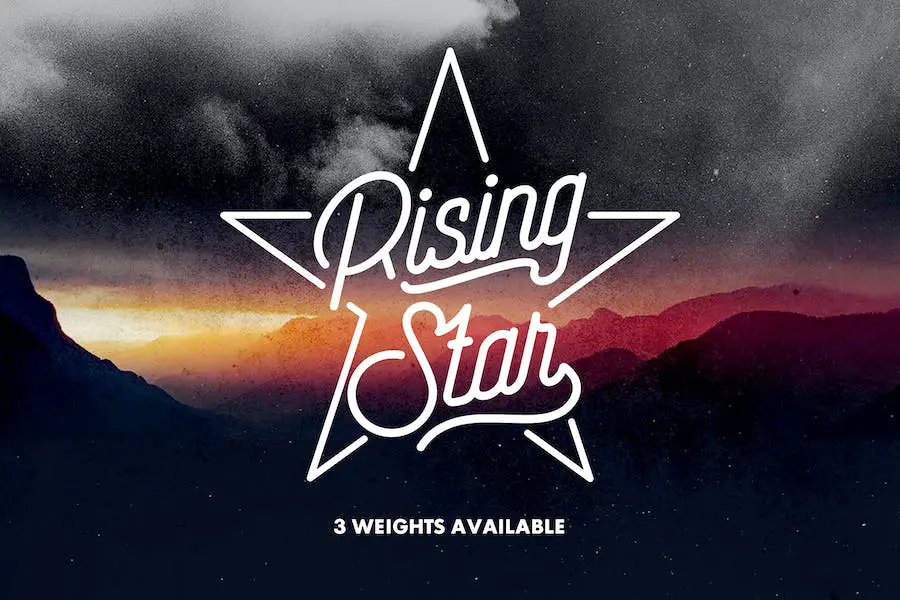
Rising Star 是一种现代单行脚本字体,捕捉了怀旧夏令营的冒险精神。 它具有常规、浅色和印花三种风格,为各种设计项目提供了多功能性。
无论您是设计网站、海报、菜单还是包装,这种字体都是完美的选择。 它结合了友好和坚固的设计以及发表声明的能力。 但它的与众不同之处在于它给任何项目带来的乐趣和兴奋。
准备好点燃您的创造力,并通过 Rising Star 为您的设计带来一丝夏日怀旧气息。
死星
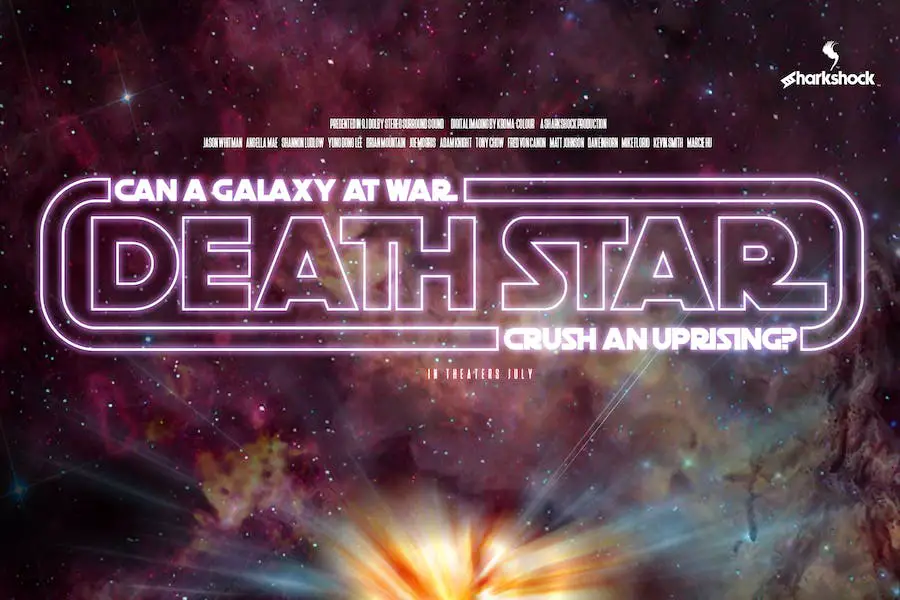
死星字体可以将您带到遥远的星系,并为您的项目提供超凡脱俗的设计。
这种全大写显示字体的灵感来自 80 年代的经典风格,具有几何圆形曲线和有限的笔画宽度变化。 它是为您的博客、徽标或 T 恤增添复古气息的完美选择。
凭借其有限的基本拉丁字符和标点符号,死星字体使事情变得简单和时尚。
星星
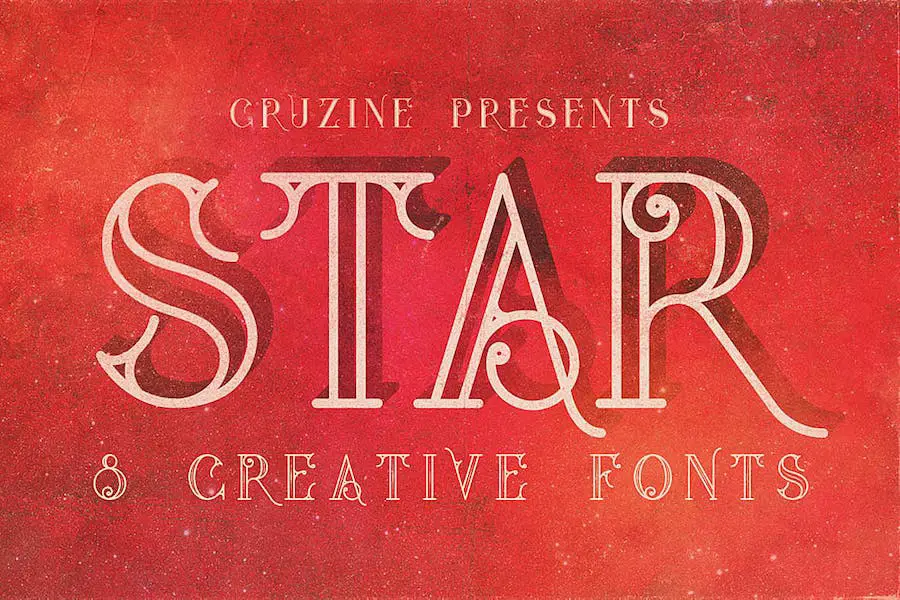
Star 是一种装饰艺术复古风格的显示或衬线字体,将为您的新项目增添一丝优雅。 无论您是从事现代设计还是创造具有复古/复古氛围的东西,Star 都能满足您的需求。
有 8 种字体文件可供选择,包括常规、grunge、内联、内联垃圾、粗体、粗体垃圾、粗体内联和粗体内联垃圾,您将有大量选项可供使用并找到最适合您的项目的字体文件。
星光
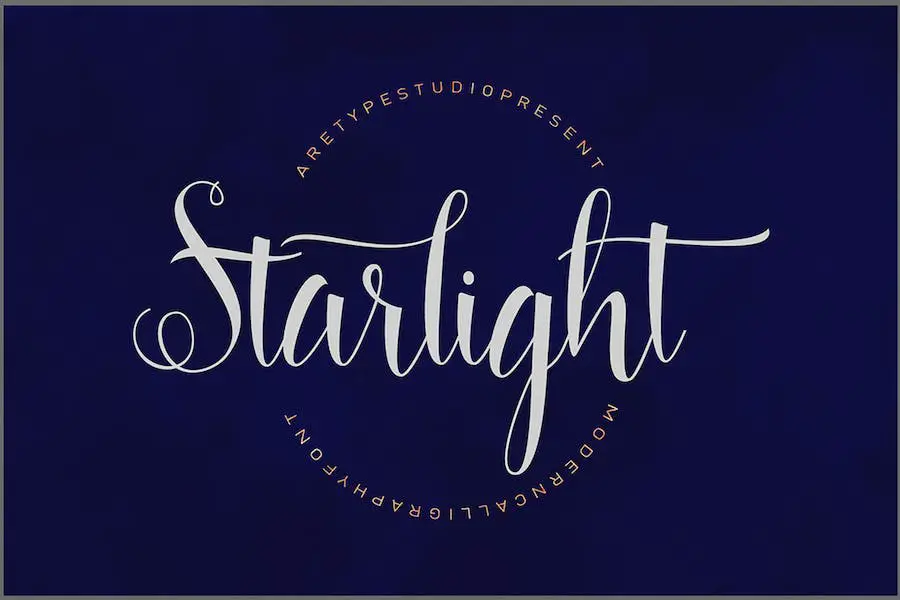
Starlight 是一种华丽的书法手稿字体,可为任何项目增添现代感。 这种字体充满活力且令人惊叹,优雅的花饰增添了一丝精致。
无论您需要签名、标题、徽标、婚礼请柬还是任何其他设计元素,星光都是完美的选择。 它还可用于时事通讯、信笺、标牌、标签、海报和徽章。
追星
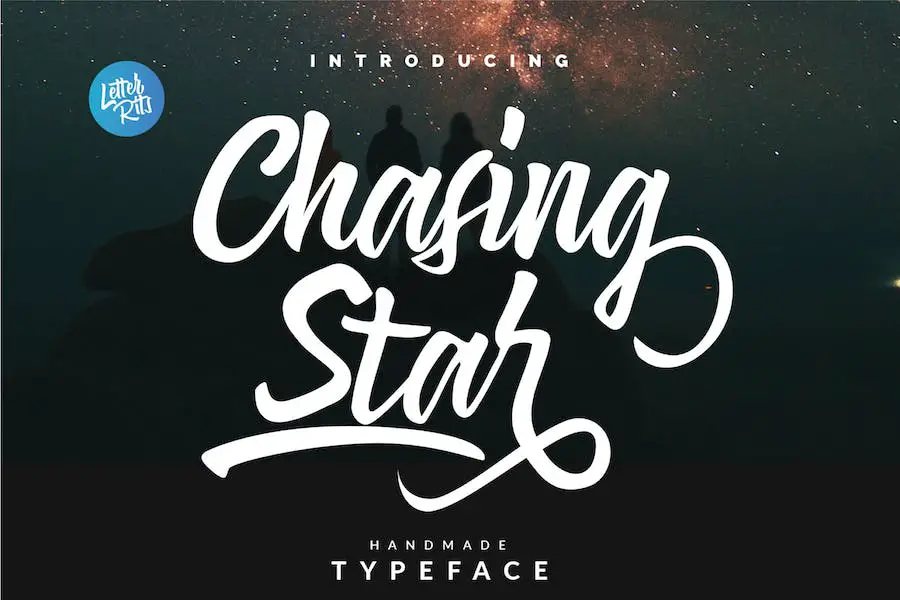
追星字体是一种多功能字体,为图形设计师提供了多种选择。 它包括大小写字母、数字、标点符号、符号和多语言字符,使其适用于广泛的项目。
无论您从事现代还是复古风格的设计,Chasing Star Font 都能为您的项目带来清新时尚的字体风格。
追星字体的关键属性之一是它适合品牌项目。 如果您想创建一个独特且令人难忘的品牌标识,这种字体可以帮助您实现这一目标。
洛维利亚星
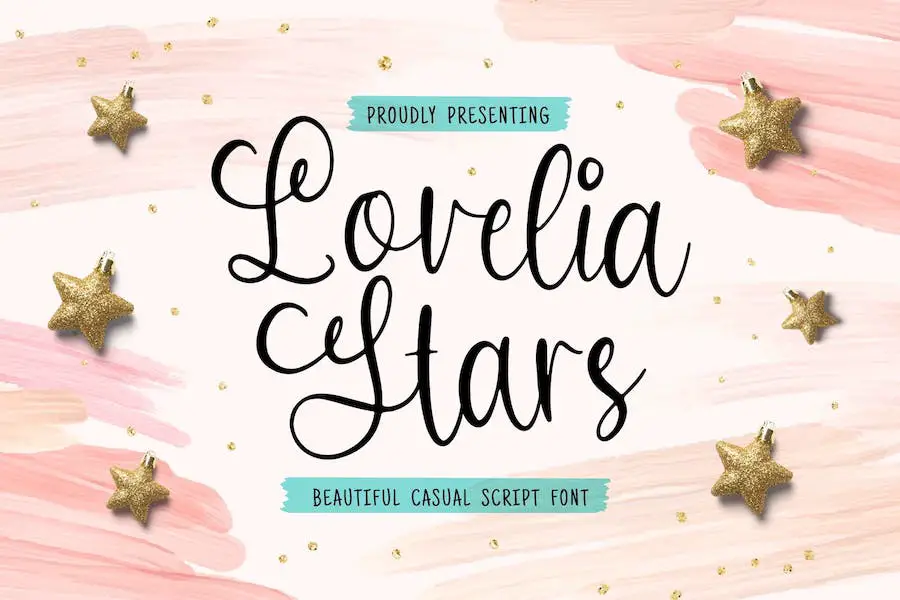
Lovelia Stars 是一种多功能字体,可以通过多种方式增强您的设计项目。
它非常适合创建醒目的徽标和品牌材料、为您的摄影添加独特的触感、制作令人惊叹的邀请函、为您的创作添加水印、制作引人注目的广告、增强产品包装以及为特殊活动增添一丝魔力。
这种字体可以满足您的所有创意需求及其他需求。
奇迹之星
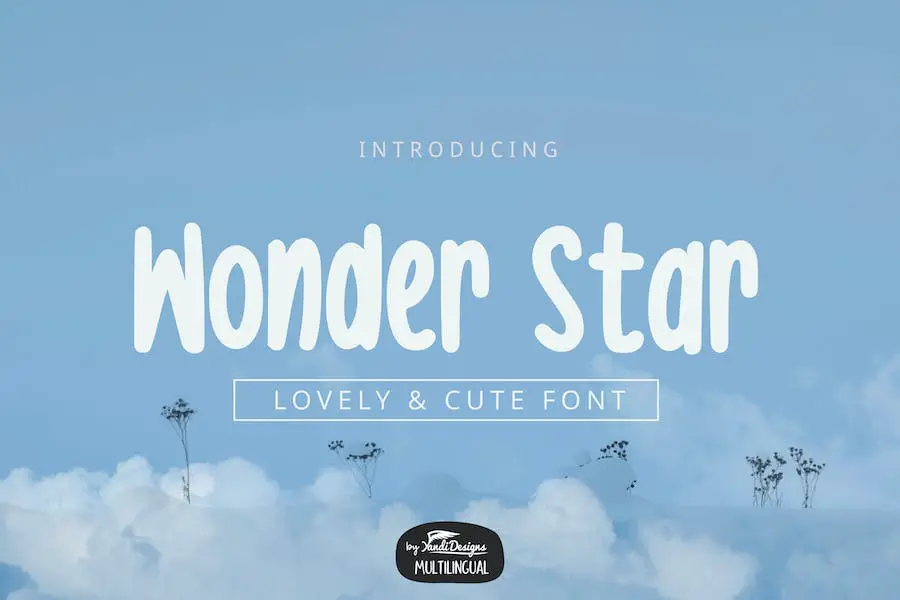
Wonder Star 是一种多功能且迷人的手工字体,可以增强各种设计项目,例如儿童书籍、引言、徽标、标题和标题。 它采用 .OTF、.TTF 和 . EOT文件格式,确保与不同设计软件的兼容性。
该字体包括基本拉丁字符、数字和符号,可以无缝集成到标准英语文本中。 此外,它还为英语、法语、西班牙语、德语、意大利语、印度尼西亚语和马来语等语言提供最少字符集的多语言支持。
借助 Wonder Star,您将可以使用各种字形,为您的设计增添俏皮和异想天开的感觉。 无论您想要创建迷人的书籍封面、引人注目的徽标还是引人注目的标题,这款字体都能满足您的需求。
闪烁之星
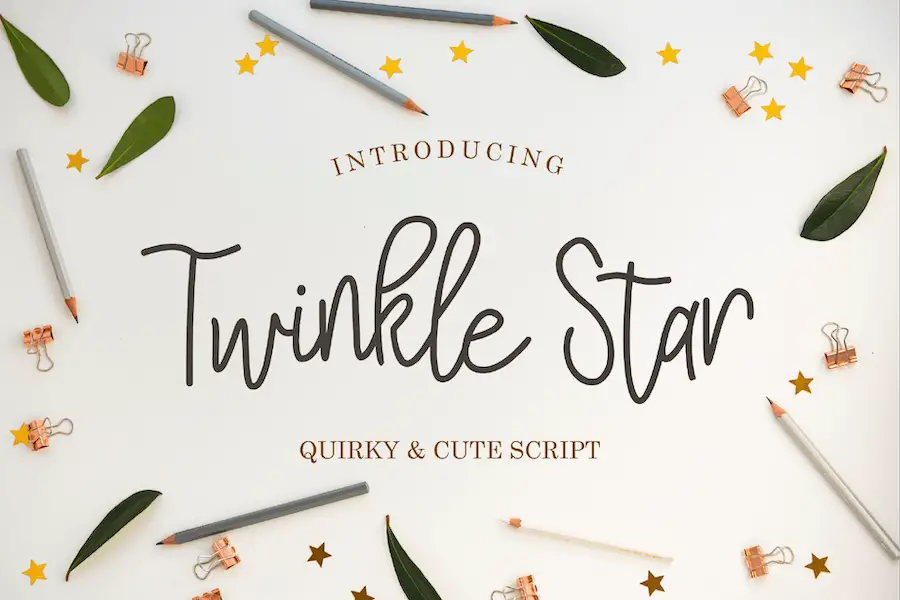
如果您想为您的设计添加古怪可爱的感觉,Twinkle Star 是必备字体。 无论是圣诞贺卡、商业徽标还是聚会邀请函,这种脚本字体都会立即赋予您的项目特色。
但这还不是全部,该字体还包含 100 多个附加字形,包括连字,并支持多种语言,例如英语、法语、西班牙语等。
Twinkle Star 的突出特点之一是其 OpenType 功能。 通过连字和替代字符,您可以轻松创建独特且引人注目的设计。
流星
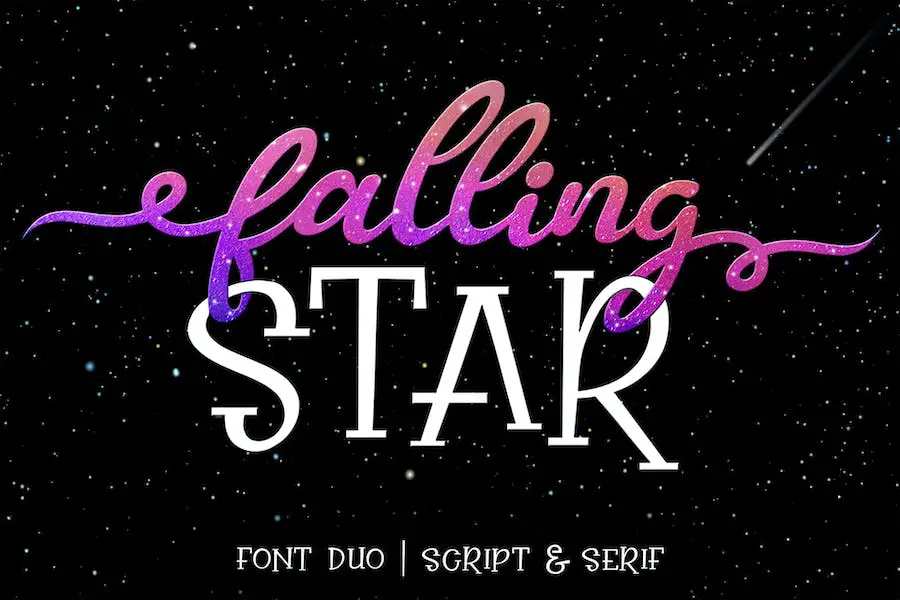
Falling Star 是一款令人惊叹且全面的字体组合,可为您的项目增添品牌而又友好的感觉。 该字体提供两种可以无缝组合或单独使用的样式,从而实现设计的多功能性。
无论您是想创建一个有凝聚力的品牌形象,还是只是想为您的作品增添一丝优雅,Falling Star 都能满足您的需求。
凭借其独特的风格组合,Falling Star 为平面设计师提供了无限的可能性。 这两种风格可以一起使用,创造出具有凝聚力和引人注目的设计,或者每种风格都可以各自闪耀,使其成为任何项目的完美选择。
星星灯
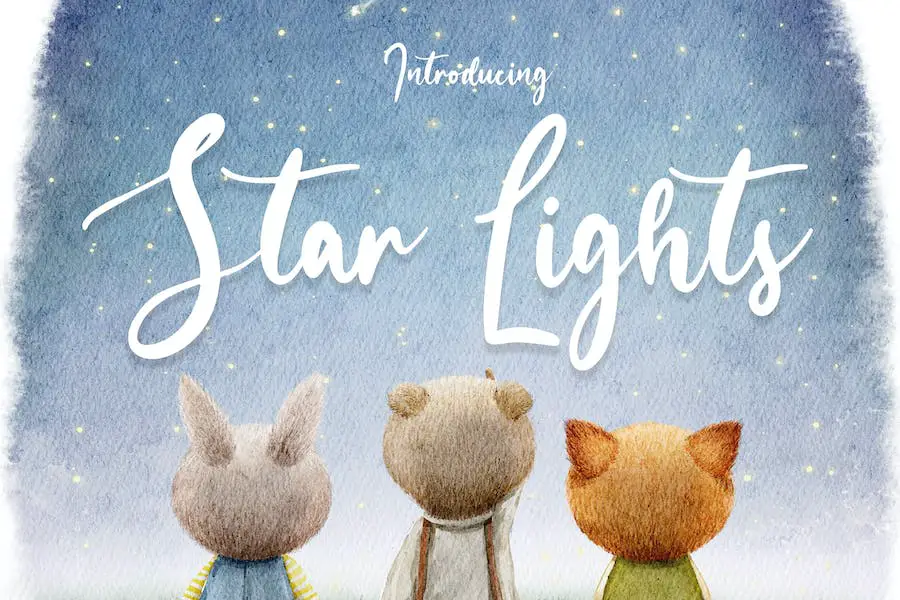
最佳免费星星字体
希望为您的设计项目增添一丝天体魔法? 别再犹豫了! 在本文中,我们将展示一些最好的免费星形字体,它们将把您的设计提升到新的高度。
所以,发挥你的创造力,让我们潜入一个充满闪烁字体的世界。 不要错过等待着您的奇迹!
星斯特雷拉
Star Strella 是 Jaime Rangel Castro 的一款新字体,对于希望将项目提升到新水平的平面设计师而言,它是一种游戏规则改变者。 凭借其独特而引人注目的设计,Star Strella 将为任何设计增添一抹优雅和精致。
这种字体拥有一系列有吸引力的属性,使其成为出色的选择。 首先也是最重要的是,其复杂且艺术的设计使其与市场上的其他字体区分开来。
美丽的曲线和对细节的关注使其成为创建令人惊叹的徽标、标题和标题的完美选择。
星盾
Star Shield 是由graphicauceco 设计的字体,非常适合想要增强项目设计的图形设计师。 它是一种易于阅读且时尚的字体,可为任何设计增添一抹专业精神。
凭借其独特的属性和时尚的设计,Star Shield 是任何想要提升作品水平的设计师的必备品。 其多功能性使其可用于各种项目,使其成为任何设计师工具包中的宝贵资产。
因此,如果您需要一种能够将您的设计提升到新水平的字体,那么 Star Shield 就是您的最佳选择。
星门
Star Doors是由Checkered Ink设计的字体。 这种字体非常适合想要增强项目设计的图形设计师。 凭借其独特而引人注目的风格,Star Doors 一定会让您的设计脱颖而出。
它用途广泛,可用于从徽标到海报的各种项目。 这种字体简洁的线条和对细节的关注使其成为任何希望为其作品增添创意的设计师的必备品。
斯塔基
Starkey 是由 Mans Greback 设计的一种字体,它将把您的图形设计项目提升到一个新的水平。 这种优雅的字体展示了简洁与精致之间的完美平衡,使其成为各种设计工作的绝佳选择。
凭借其简洁的线条和独特的特点,Starkey 为任何项目增添了现代感和专业精神。
Starkey 的突出特点之一是其多功能性。 无论您是在进行徽标设计、网站布局还是印刷广告,该字体都可以轻松适应任何风格或主题。
星7
Star7 是一种非常适合希望为他们的项目增添一些风格的图形设计师的字体。 凭借其独特而引人注目的设计,Star7 一定会让任何设计脱颖而出。
其大胆而简洁的线条使其可用于各种设计应用。 无论您是创建海报、徽标还是网站,Star7 都会为您的项目带来额外的创造力和专业性。
该字体由 GFR Creative 创建,是任何希望将其项目提升到新水平的设计师的必备字体。
经常问的问题
星形字体是一种装饰字体,以各种形状的星形作为字符。 它们可以用来为您的设计项目增添异想天开和神圣的感觉。
使用星形字体可以为您的设计添加独特且引人注目的元素。 无论您是创建邀请函、海报、徽标还是社交媒体图形,星形字体都可以帮助您创建具有视觉吸引力且令人难忘的作品。
结论
在本文中,我们探索了 15 种最适合图形设计师的明星字体,以增强他们的项目设计。 从优雅而精致的选项到有趣而异想天开的选择,我们涵盖了一系列必将提升您的设计的字体。
无论您是在寻找免费选项还是愿意投资高级字体,我们都会为您提供 2023 年最好的明星字体。